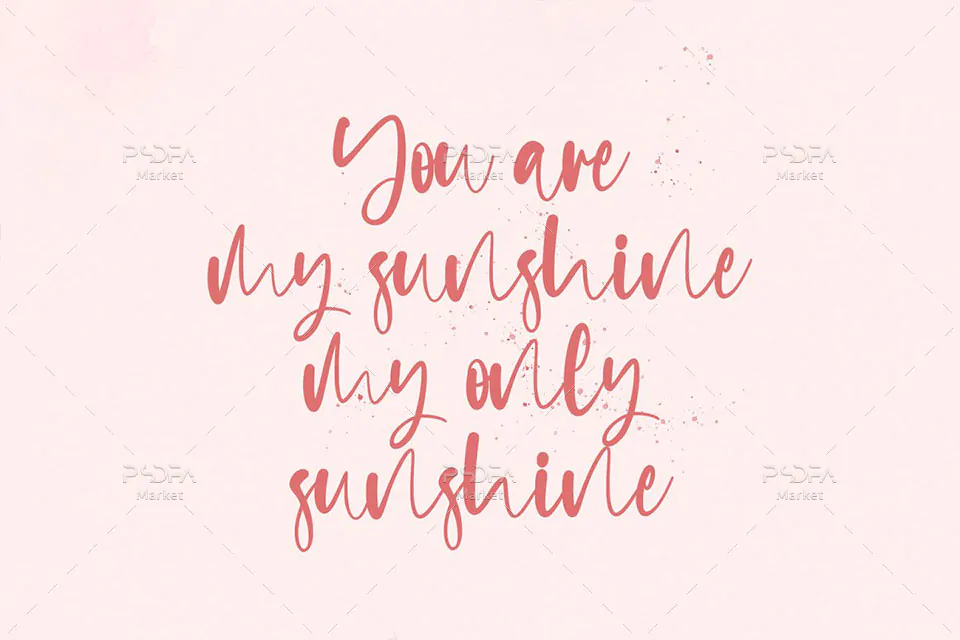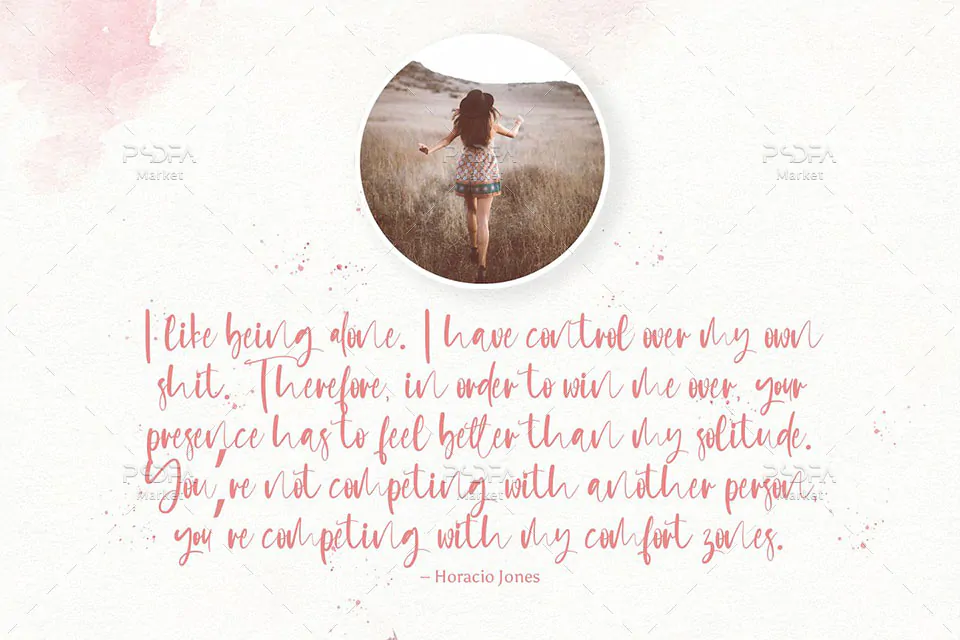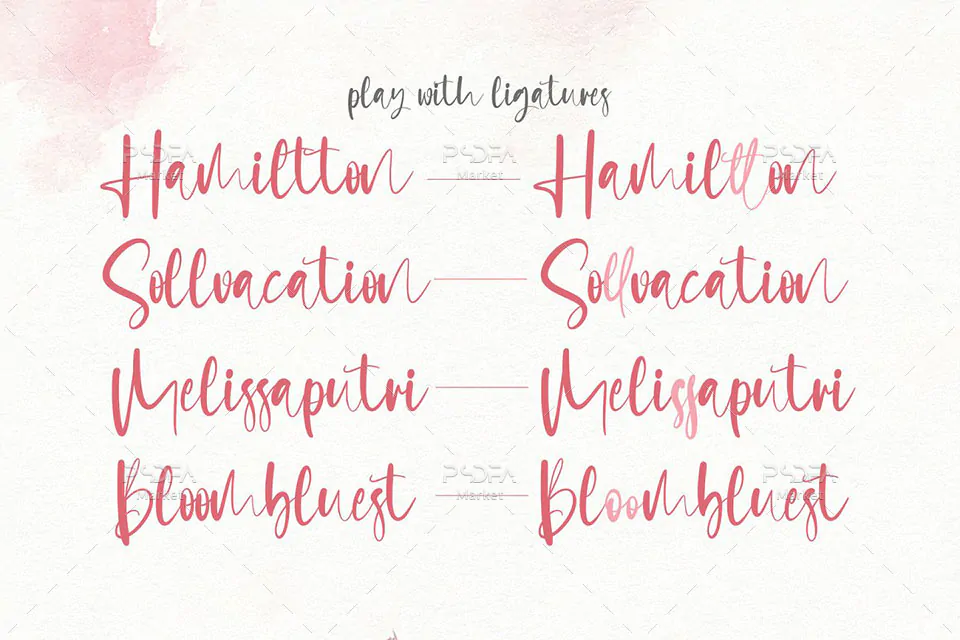
فونت رمانتیک و عاشقانه دستنویس انگلیسی Saturday Crush
فونت رمانتیک و عاشقانه Saturday Crush
فونت رمانتیک و عاشقانه دستنویس انگلیسی Saturday Crush یک قلم زیبای سرهم نویسی فوق العاده زیبا است که مناسب جهت استفاده در طرحهای گرافیکی مختلف به خصوص طراحی انواع کارت تبریک میباشد. این فونت زیبا در قالب 2 فایل OTF, TTF در فایل محصول قرار دارد که با نصب یکی از این 2 فرمت در پوشه فونتهای سیستم میتوانید از این فونت انگلیسی در تمام نرم افزارهای گرافیکی و تایپ متون همچون فتوشاپ، افتر افکت، پریمیر، ورد، پاورپوینت و … استفاده کنید.
فونت انگلیسی Saturday Crush در وزن معمولی (Regular) طراحی شده است که میتوانید از آن در طراحی انواع کارت تبریک، کارت پستال، کارت ویزیت، کارت عروسی، کاور آلبوم موزیک، طراحی انواع بنر، پوستر، تراکت، تقویم و دیگر طرحهای گرافیکی استفاده کنید.